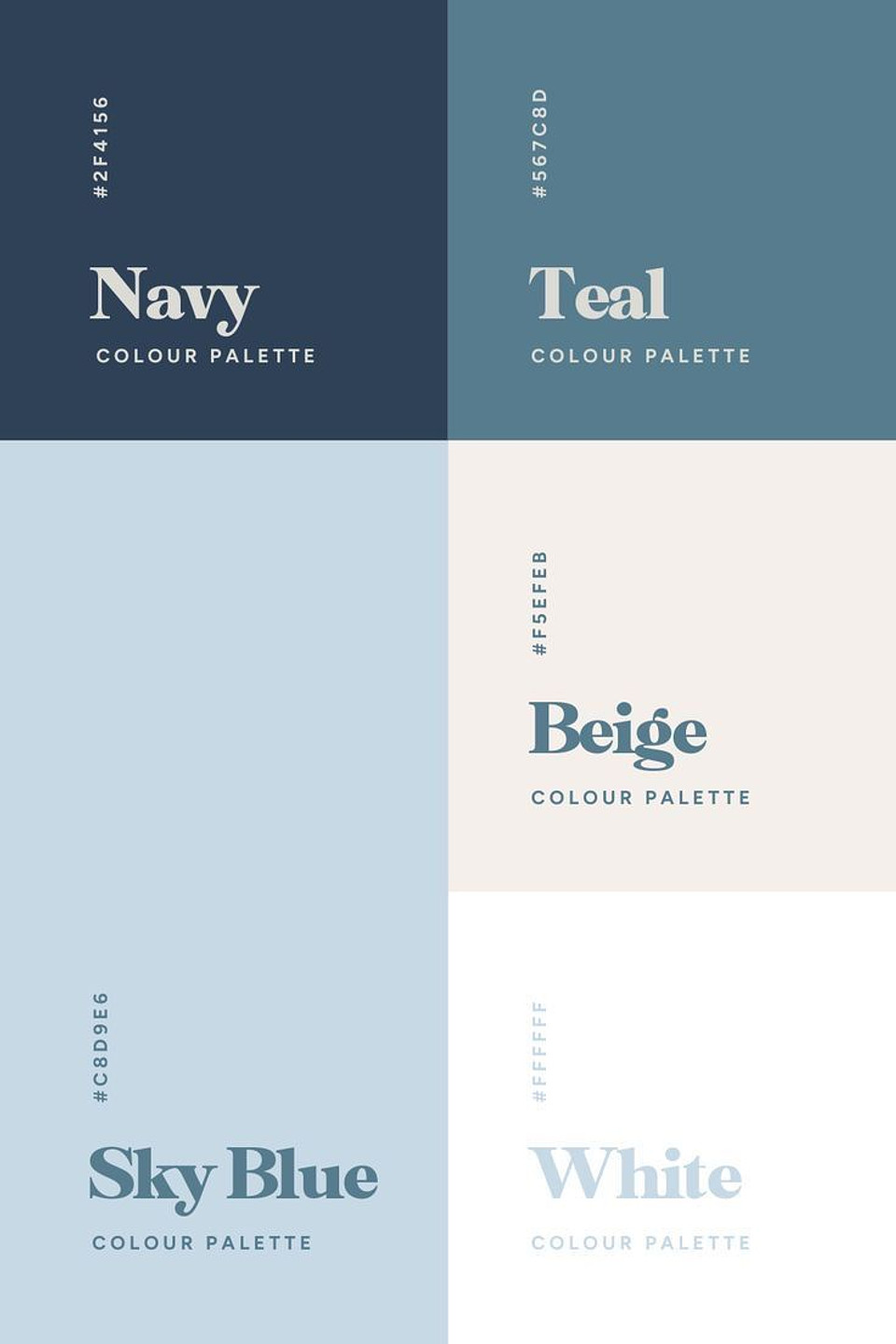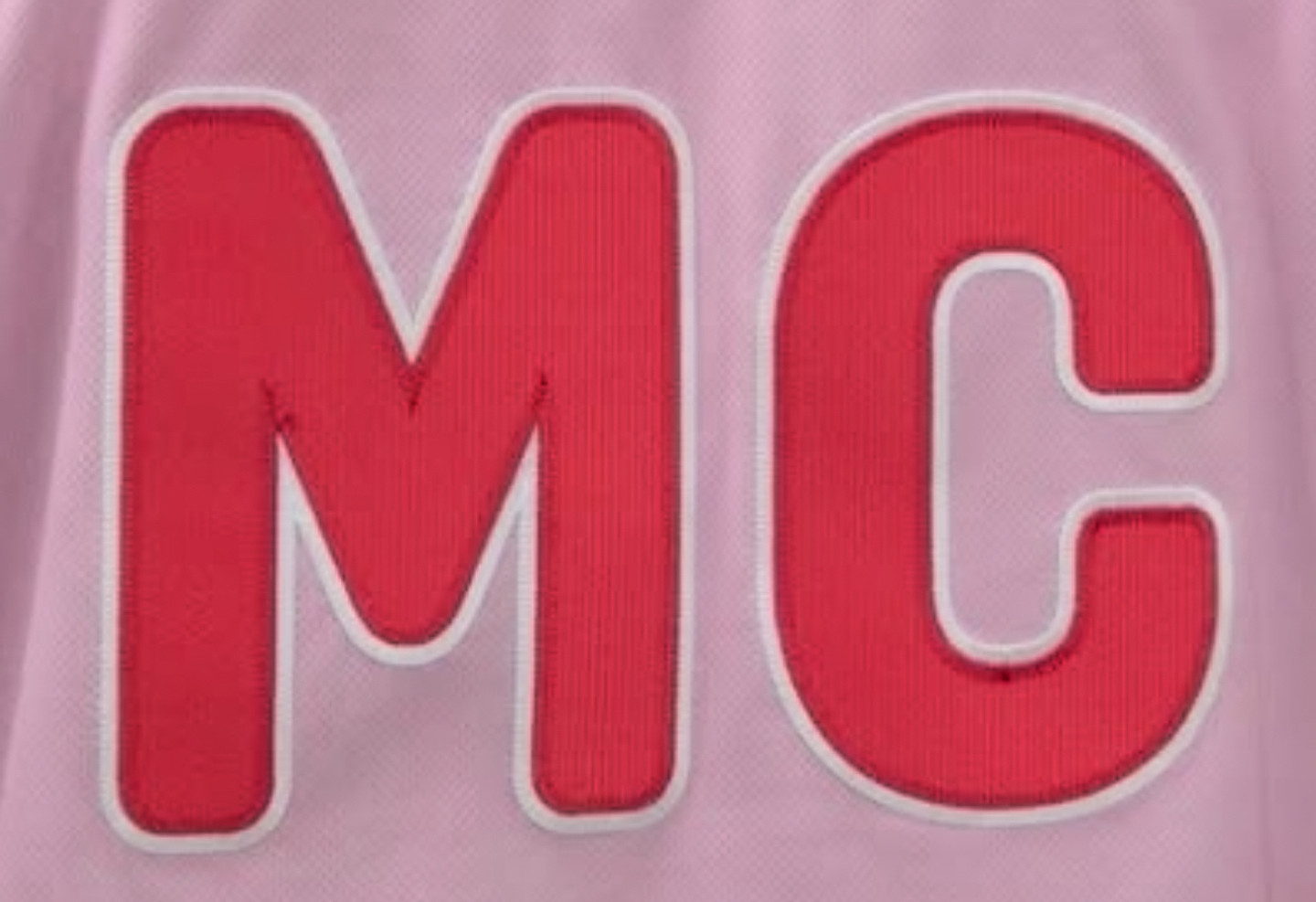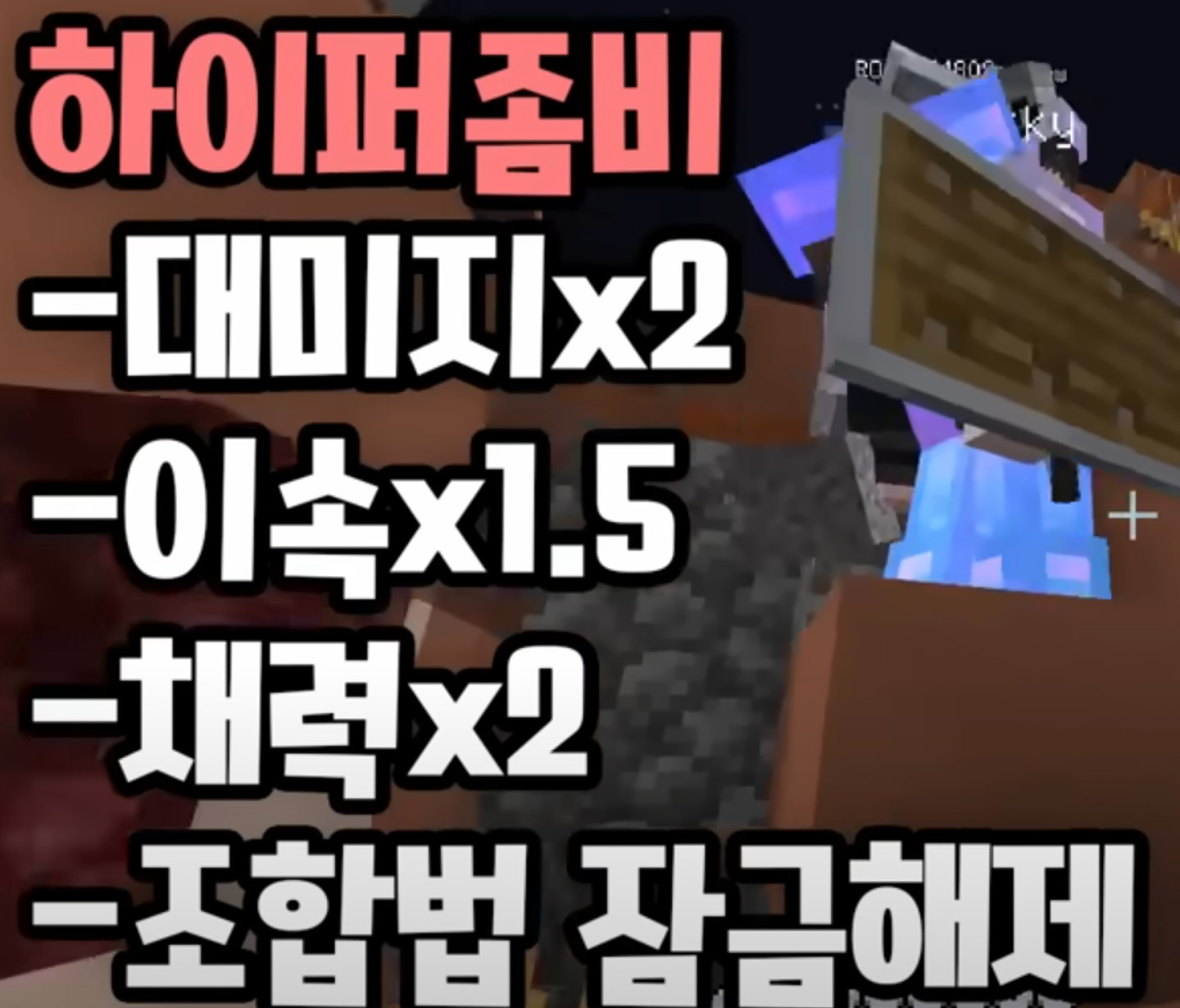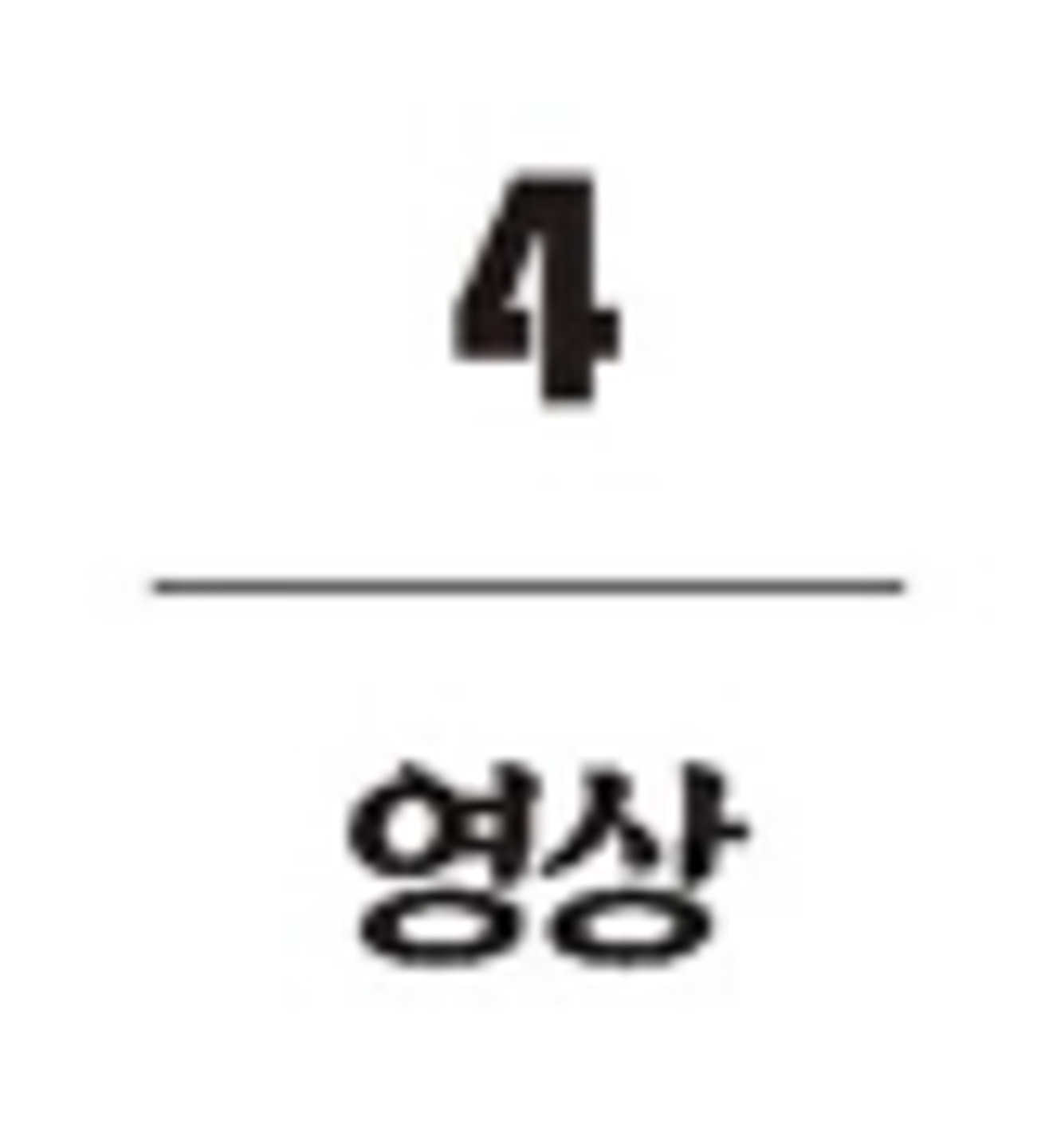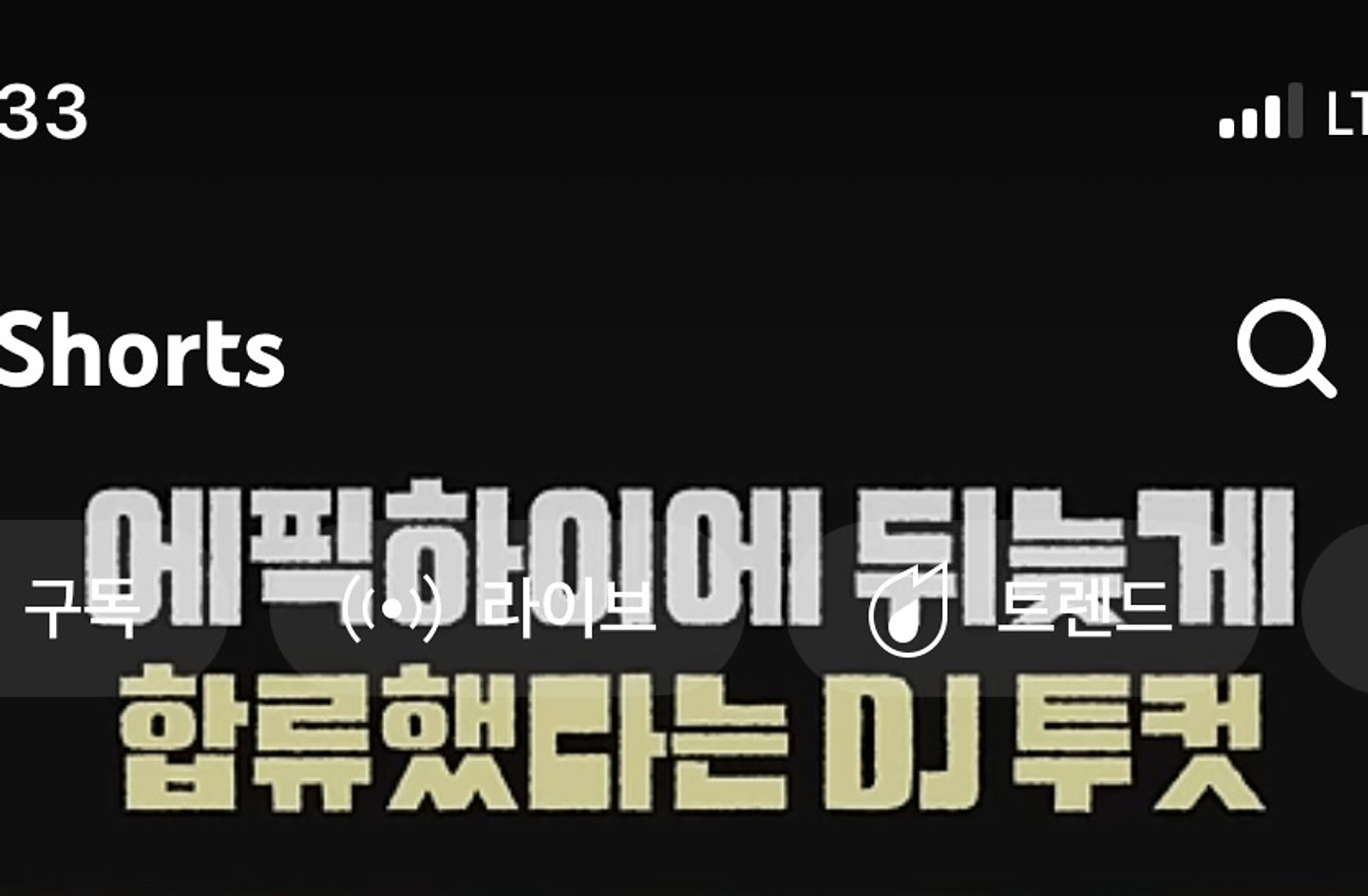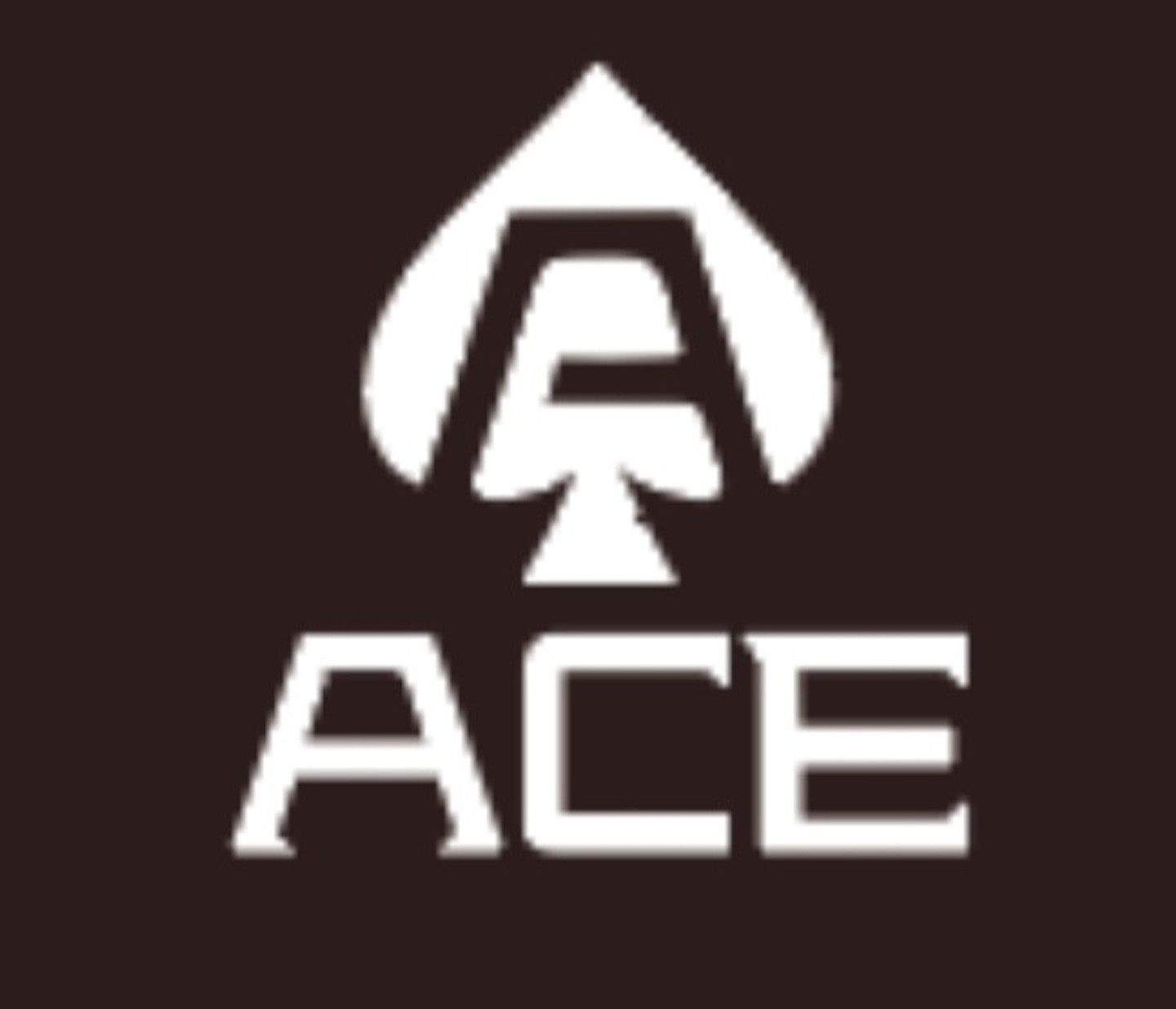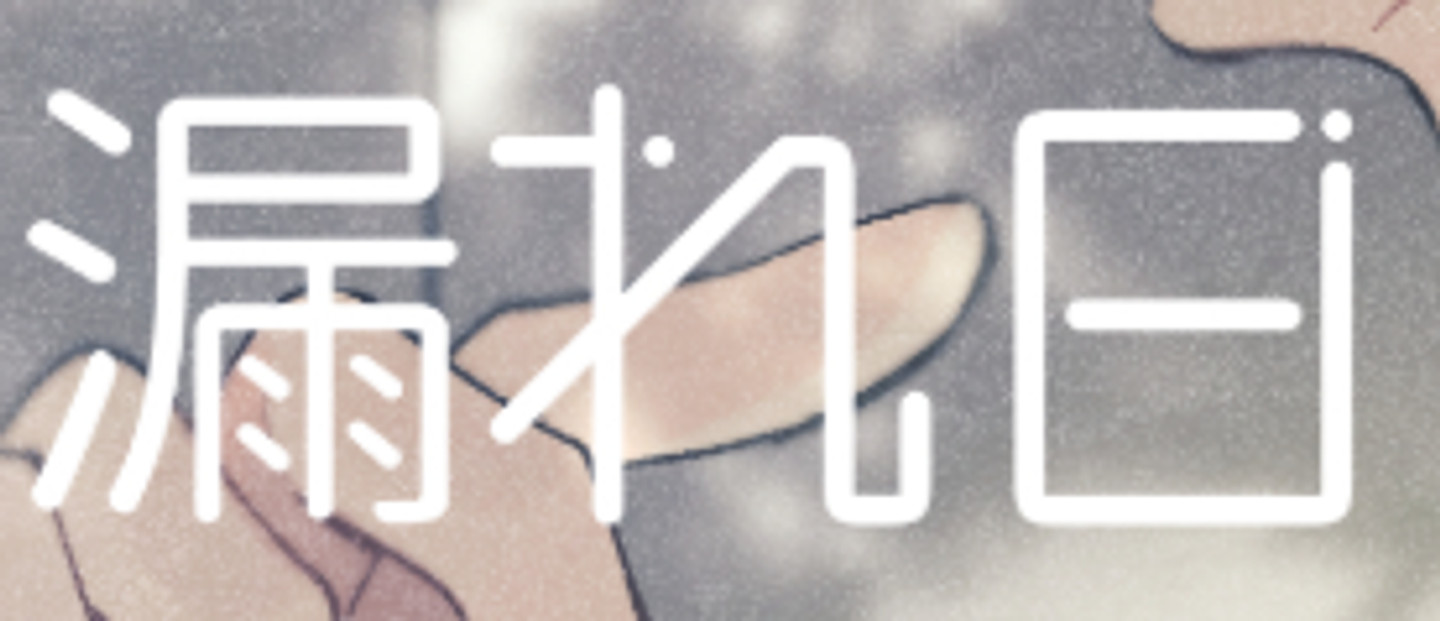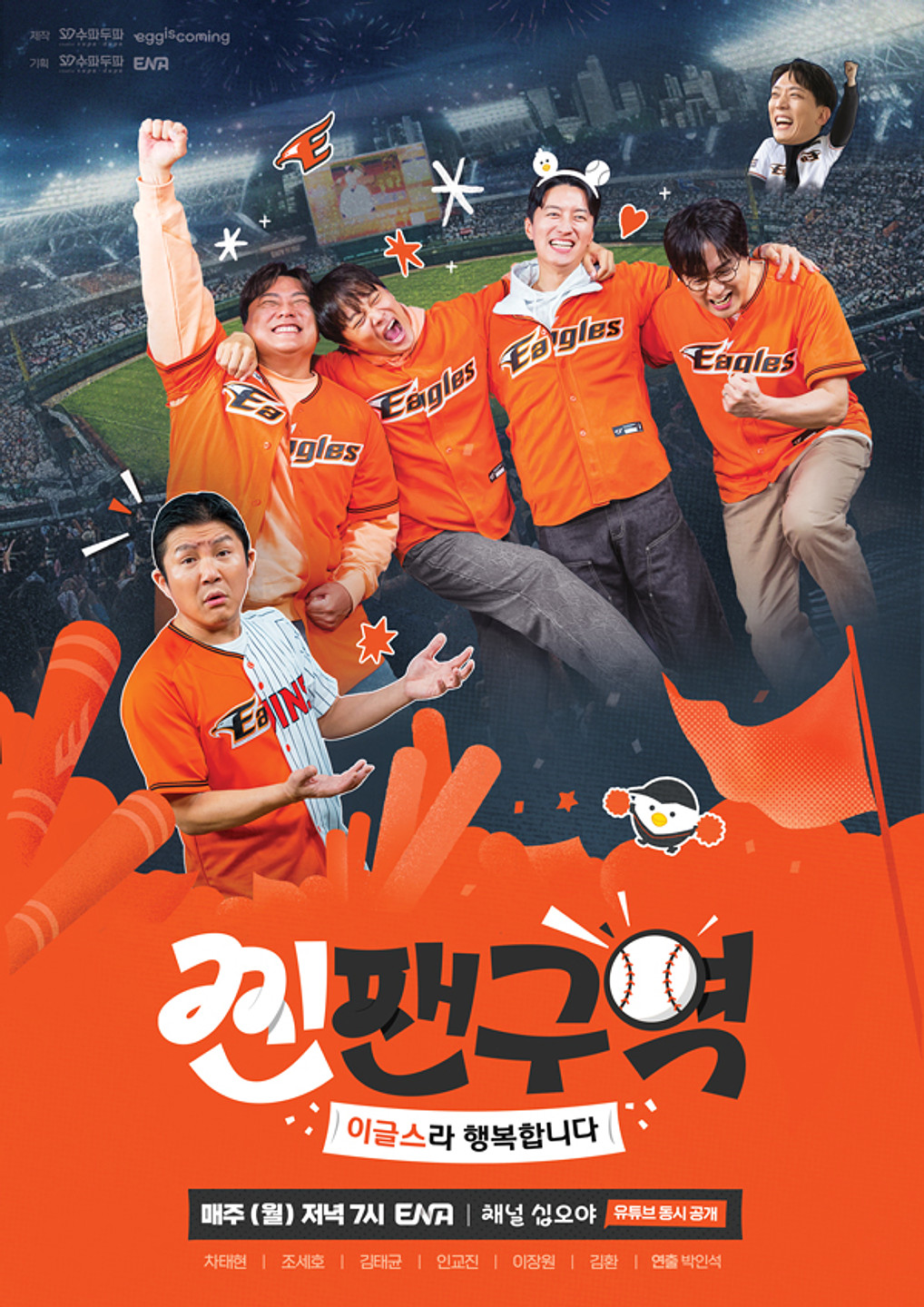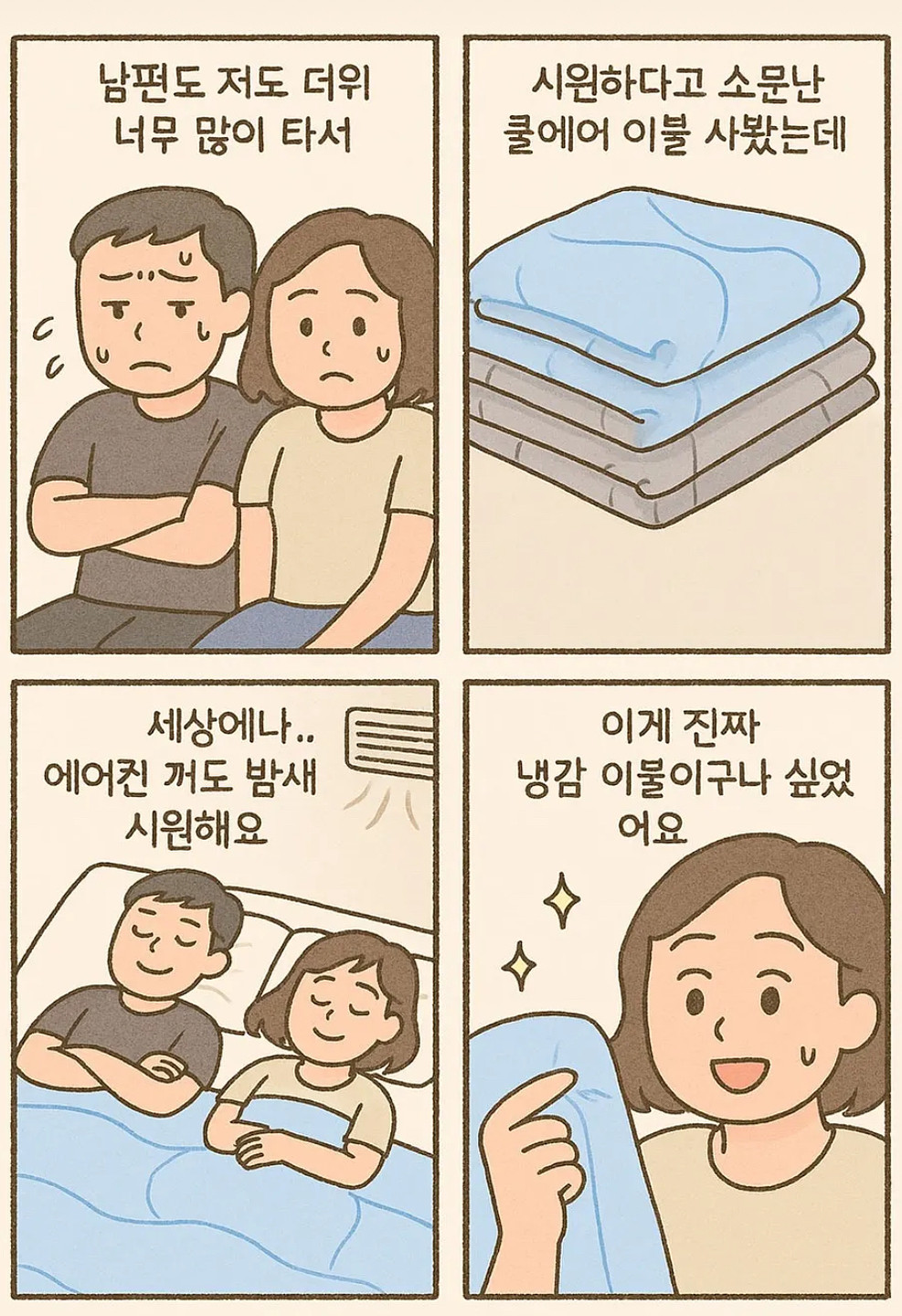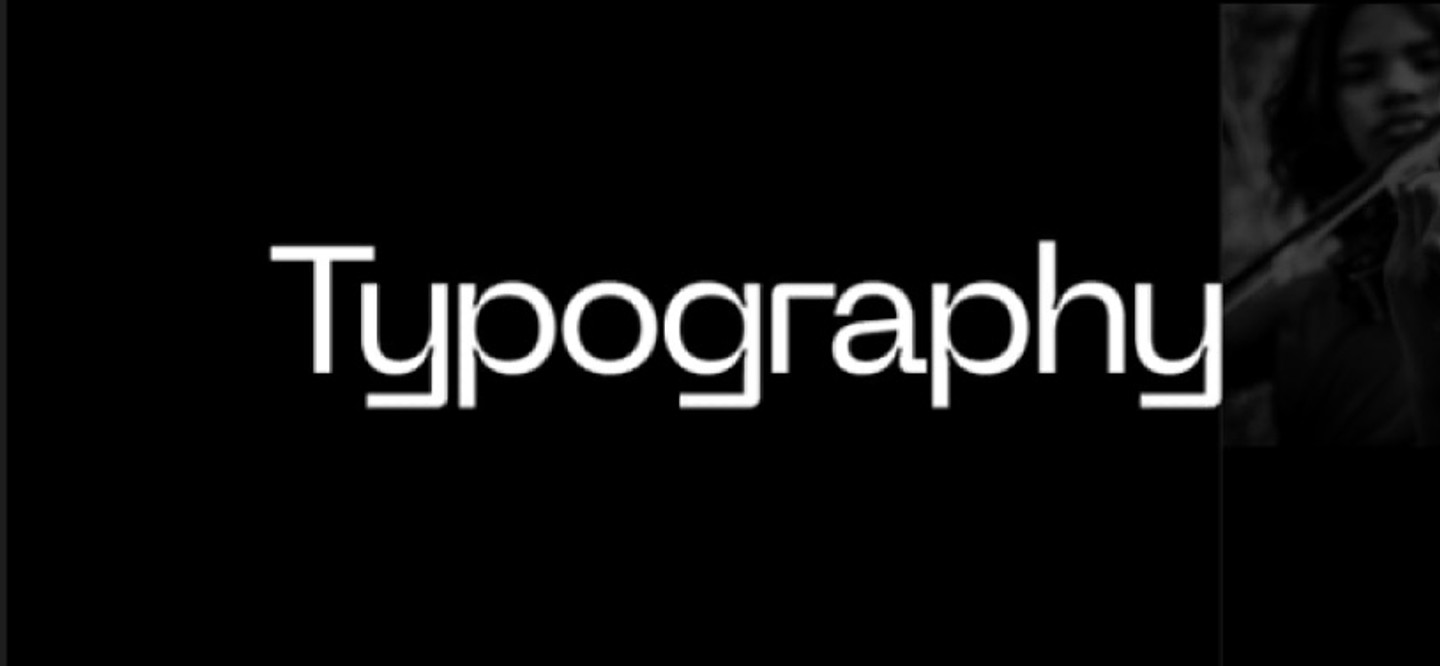
아무리 찾아봐도 안 나옵니다 🥺
해당 폰트가 궁금합니다!
이미지같은 폰트나 비슷한 폰트 알려주시면 감사하겠습니당
폰트알려주세요
무슨 서체인지 궁금합니다.
안녕하세요~ 여기에 사용된 폰트 스타일이 무엇인지 궁금해요! 끝이 둥글둥글한데 비슷한 폰트는 좀 있지만 결국 못 찾고 있어요 ㅜ 고수님들의 도움을 요청드려봅니다~~ㅠㅠ
서체 뭘까요? 넘 예뿌네요...
이 폰트 정보 아시는분있나요? 클립아트코리아에서 소스제작시 많이 사용하는것같아요
이 폰트 혹시 뭘까요?
이거 무슨 폰트일가요?
이 폰트 궁금해요!
안녕하세요 이글씨체 폰트와 어떤 포인트를 준건가요? 반짝이?
Happy wedding Day에 쓰인 영문 폰트가 궁금합니다
자막 무슨 폰트일까요?
유튜브 보는데 자막 너무 궁금해요!!ㅠㅠ
이거 폰트좀 알려주세요
폰트 정보 너무너무너무너무 궁금해요
무슨 폰트인지 찾고있어요!! ㅠㅠ 아시는분 계시려나요? 찾기 어려워서 질문드립니다!
폰트 찾기
고전체 같은데 무슨 폰트인가요 ㅠㅠㅠ
글씨체 뭐였는지 기억이 안나요ㅠ
혹시 이 폰트 아시는 분 계실까요? ai한테 물어도 답을 찾을 수 없어서 여기 척척박사님이 계실까 싶어 올려봅니당…!!
비슷한 글씨체 있을까요?
무슨 폰트야?
이 폰트 이름 뭘까요?
바깥으로 삐쭉삐쭉 나왔어요
영어 폰트 이름 알려주세요ㅜㅜ
이 폰트 너무궁금합니다
이거 무슨 폰트인가요? ㅠㅠ
이 폰트 궁금해용..! 아시는 분 계신가요??
이 폰트가 뭔지 찾아 헤매고 있습니다 아시는 분,, 🥺
발젭님 폰트
위, 아래 폰트는 무엇일까요?
글씨체 궁금합니다!!!!
옛날 잡지에서 종종 보였던 폰트인데 무슨 폰트일까요? 유리구슬체랑 마포홍대프리덤체는 아닌거같아요
폰트 아시는 분 ㅠㅠㅠ 알려주세요!!!!! 감사합니다.
뭔가요
이 폰트 무슨 폰트일까요? 페이퍼로지도 아닌 거 같고 지마켓 강원튼튼 다 아닌 거 같은데 궁금합니다!
하준이의 첫생일 이 폰트 뭐였죠? 생각이 날듯말듯하네요ㅠ 예전에 많이 썼던 폰트인 것 같은데
butcher vanity 글씨체 뭔가요
눈누에서 캡처했던 것 같은데 찾아지질 않네요 ㅜㅜ
우연히 보던 폰트인데 어떤건지 알수있을까요?
아니 요즘 편집할 때 다들 이 폰트 쓰시던데 대체 무슨 폰트죠…? ㅎ하 검색해도 진짜 못찾겠어ㅛㅜㅜㅜㅜ
/폰트 뭘까요?